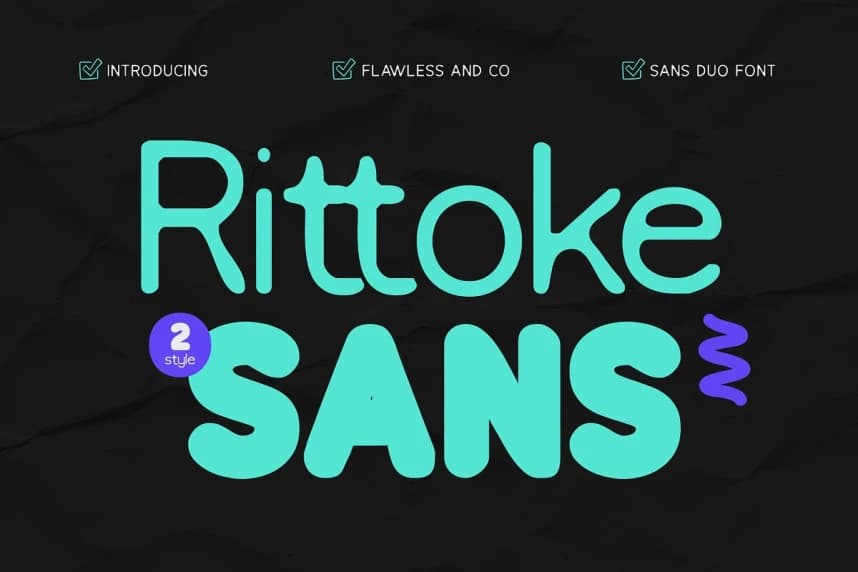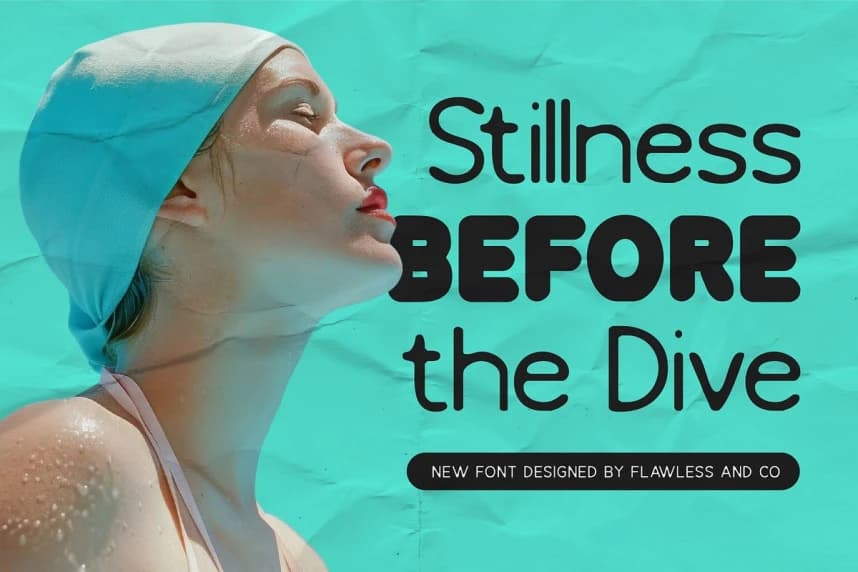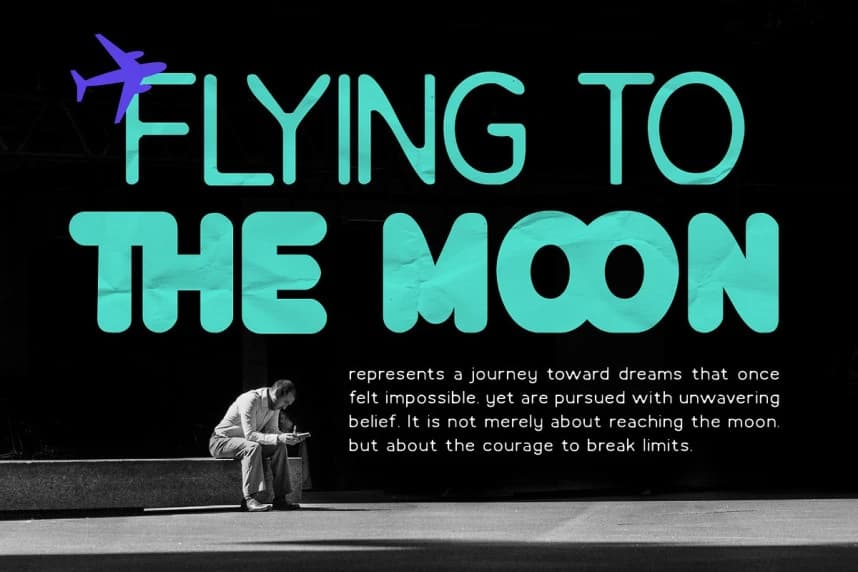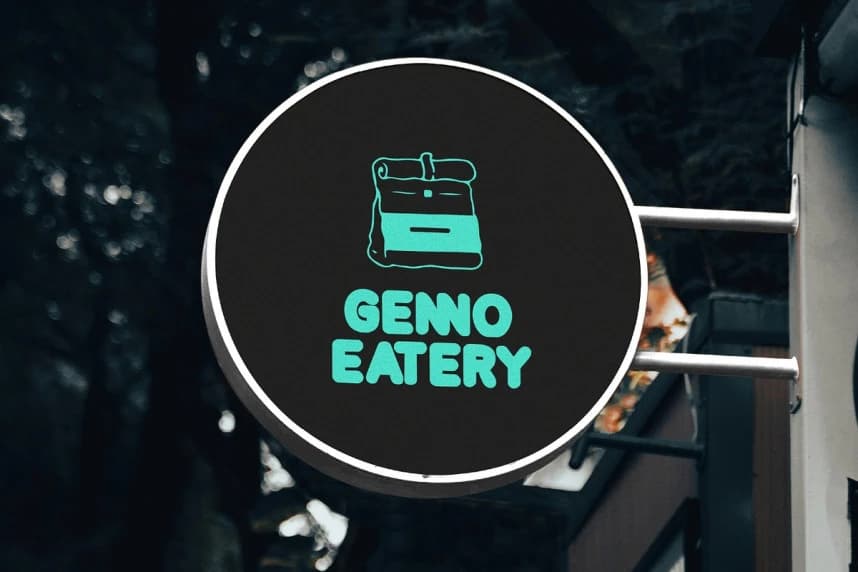
Rittoke Font
Rittoke Font, ince ve kalın stillerin mükemmel bir kombinasyonunu sunan modern bir sans serif çift tipografisidir; güçlü kontrast ve görsel hiyerarşi yaratmak üzere tasarlanmıştır. İnce sürüm temiz, zarif ve minimalist bir his sunar.
Rittoke Font, ince ve kalın stillerin kusursuz bir kombinasyonunu sunan, güçlü kontrast ve görsel hiyerarşi oluşturmak üzere tasarlanmış modern bir sans serif çift yazı tipidir. İnce sürüm temiz, zarif ve minimalist bir his sunar.